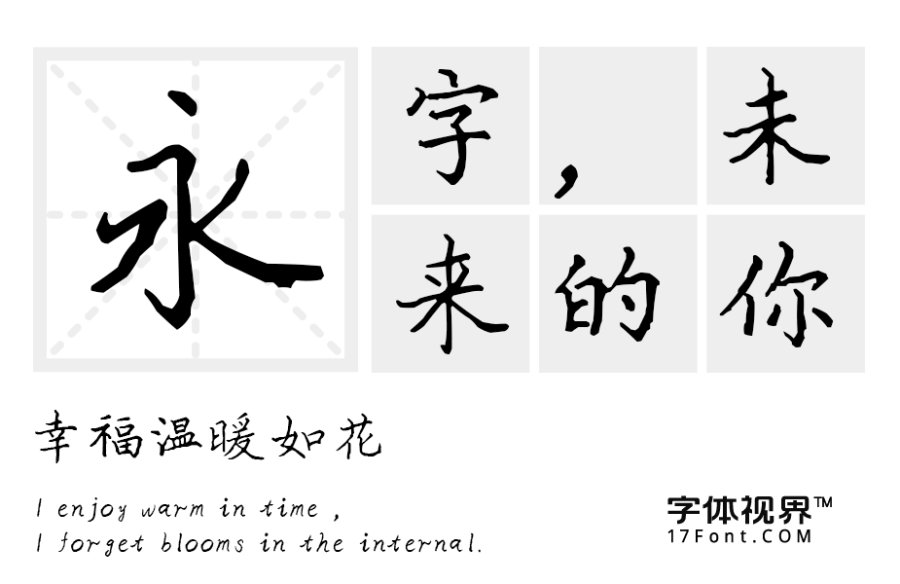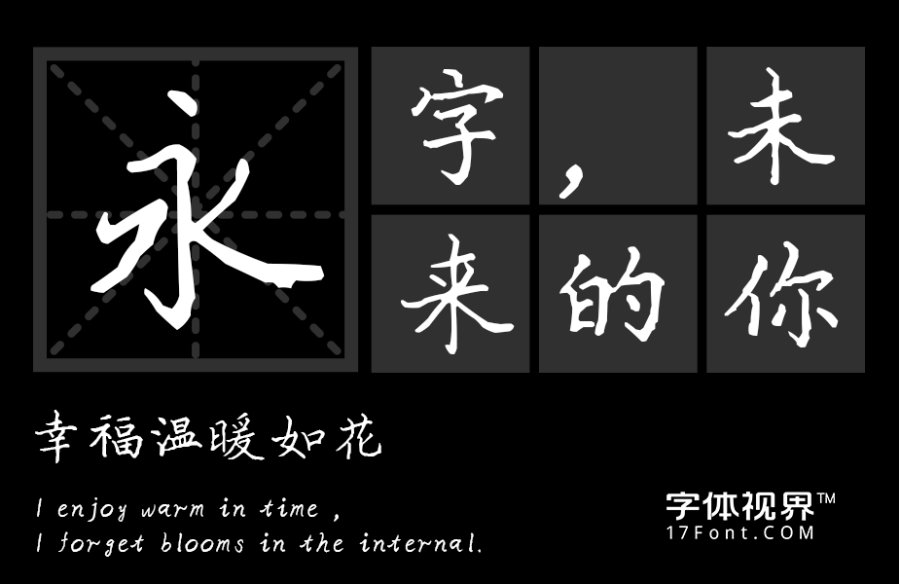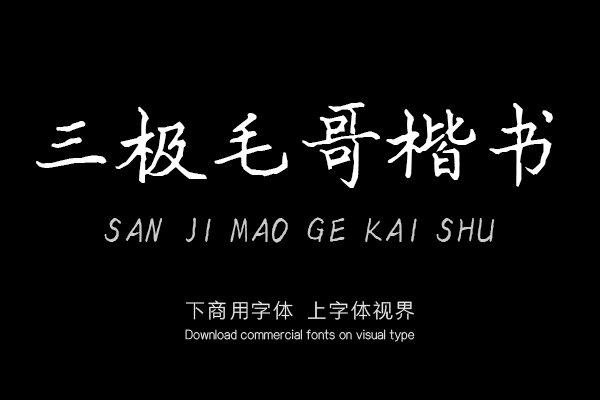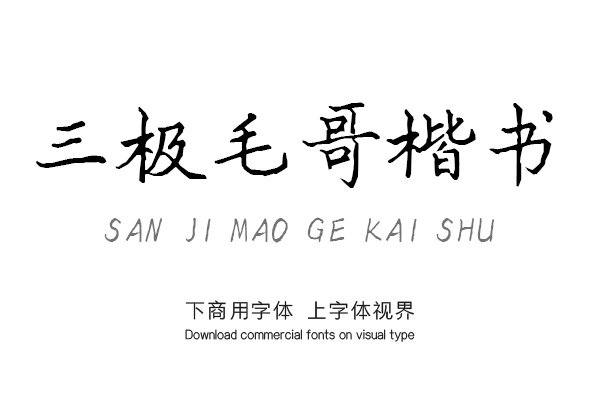
三极毛哥楷书结构严谨,既有颜体的雄浑,又不失赵体的飘逸。严谨秀气而从容和优雅,让人赏心悦目,百看不厌。可广泛用于书刊、广告、包装、影视以及社交网络个性化用字。购买须知:“下载服务费”与“字体VIP”所获得字体 仅用于个人非商用, 商用请联系付费授权。本字体为电脑用字,手机没有root权限不支持直接手机换字(手机如何root,请自行百度搜索教程)。购买前请先 了解清楚后再付款 ,字体为虚拟产品无法回收 一旦购买不支持退款。